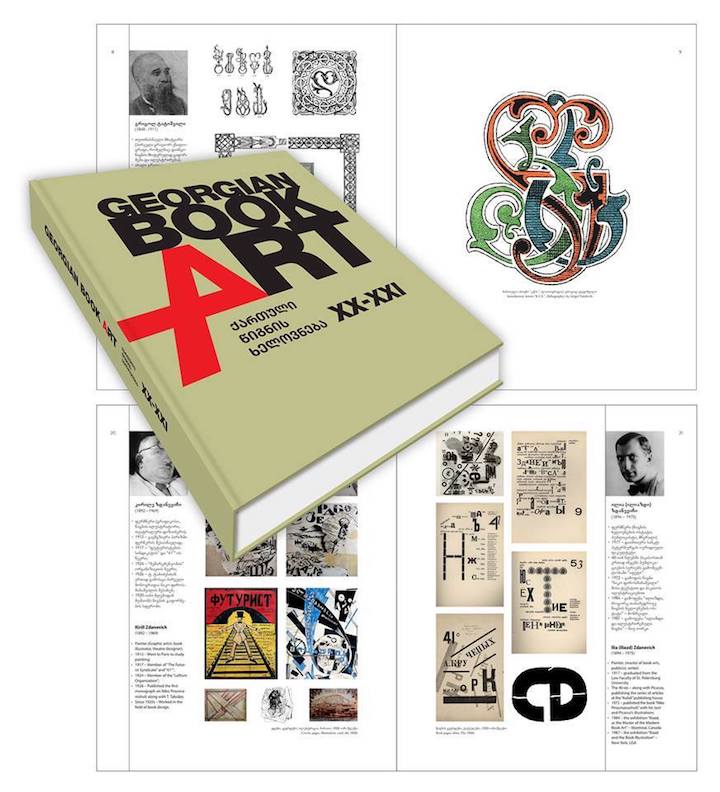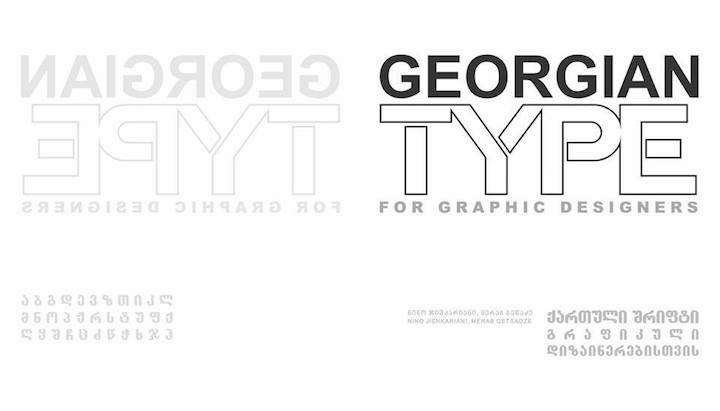
ფრანკფურტის წიგნის ბაზრობაზე საქართველოს განათლების, მეცნიერების, კულტურისა და სპორტის სამინისტროს სამეცნიერო, სამეცნიერო-პოპულარული და საგანმანათლებლო ლიტერატურაა გამოფენილი, მათ შორის კი, წიგნები: „ქართული შრიფტი გრაფიკული დიზაინერებისთვის“, რომლის პრეზენტაციაც 14 ოქტომბერს გაიმართება წიგნის ბაზრობაზე და „ქართული წიგნის ხელოვნება“.
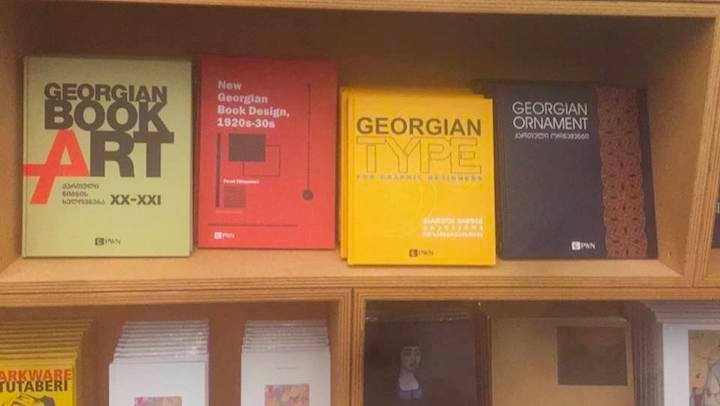
წიგნის „ქართული შრიფტი გრაფიკული დიზაინერებისთვის“ ავტორები არიან: ნინო ჯიშკარიანი და მერაბ გეწაძე. წიგნი ორენოვანია და განკუთვნილია გრაფიკული დიზაინერებისა და ქართული ანბანის გამოყენებით დაინტერესებული პირებისთვის, როგორც პრაქტიკული სახელმძღვანელო.
„ქართული შრიფტი გრაფიკული დიზაინერებისთვის“ 198 გვერდიანია და შედგება ოთხი ნაწილისაგან: მისი პირველი ნაწილი დათმობილი აქვს ტექსტს, ქართული შრიფტის შესახებ მოკლე მიმოხილვასა და განვითარების გზის მოკლე ისტორიას.
წიგნის ძირითად ნაწილს წარმოადგენს მეორე, პრაქტიკული სახელმძღვანელო გრაფიკული დიზაინერებისთვის, რომელიც ეხება ქართული ასონიშნების აგებისა და სიბრტყეზე განთავსების წესებს.
თითოეული გვერდის შუა ნაწილში მოცემულია მხედრული ანბანის ჩვეულებრივი (პატარა) ასო და მისი აგებისა და გამოყენების წესი, როგორც ქართული თანამედროვე მართლწერის ნორმატიული წესი. ხოლო გვერდის კიდეში, ლურჯ კვადრატებში მოცემულია ასომთავრული, ნუსხური და მხედრულის მთავრული ასონიშნები.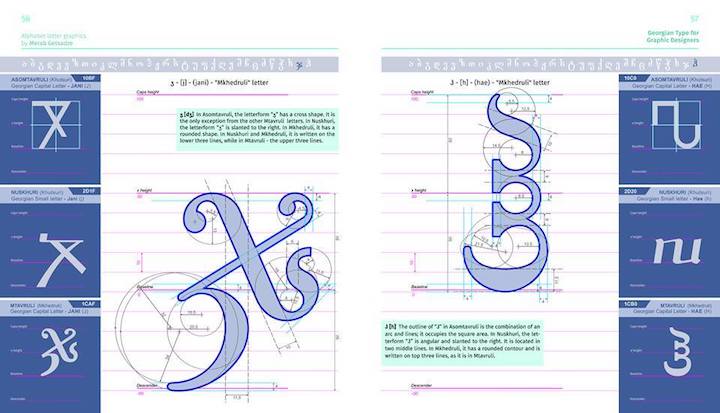
წიგნის მესამე ნაწილში მოცემულია ფართოდ გავრცელებული ძველი, ხელით შექმნილი ქართული შრიფტების გარნიტურები, ხოლო მეოთხე ნაწილში ზოგადი წარმოდგენის შესაქმნელად, მოცემულია ქართული შრიფტი დღეს და მისი გამოყენების მაგალითები პრაქტიკაში.
რაც შეეხება „ქართული წიგნის ხელოვნებას“, მისი ავტორი ნინო ჯიშკარიანია. წიგნში ისეთი მხატვრების ბიოგრაფიებია წარმოდგენილი, რომლებიც უშუალოდ, წიგნის მხატვრობაზე მუშაობდნენ. გარდა ამისა, წიგნში ნახავთ ქართულ შრიფტს, ილუსტრაციებს და ა.შ.